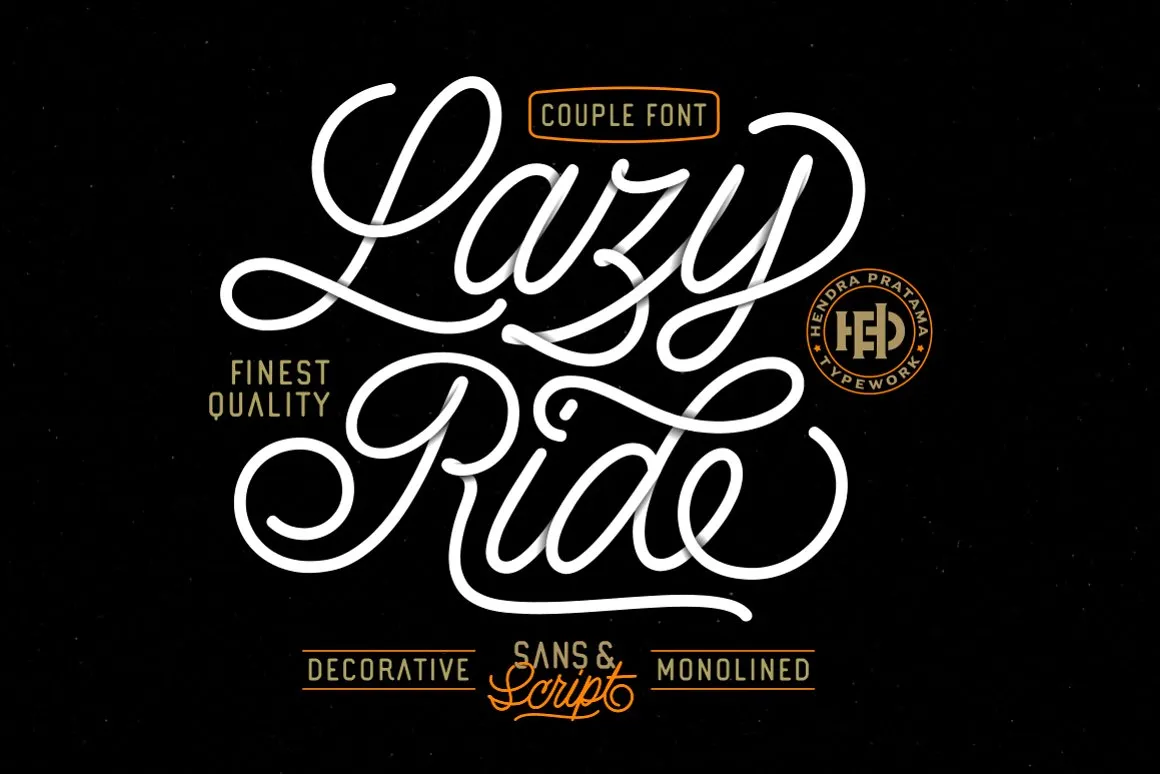
Descubra a nova adição para seus projetos de design com Lazy Ride Script Font, uma fonte script premium criada por Hendra Pratama que agora está disponível gratuitamente. Esta fonte é perfeita para aqueles que precisam dar um toque de ternura aos seus trabalhos. Ela combina muito bem com outras fuentes e pode adicionar o estilo necessário ao seu projeto. Lazy Ride Script contém mais de 670 glyphes, está disponível em formato OpenType e possui atribuição Unicode PUA (Personal Use Agreement). O uso alternativo dos glyphs é dividido em várias fechas de características do OpenType: Alterações Estilísticas, Características Contextuais, Espalhamento, Ligaturas e Conjunto de Alteração Estilística. No conjunto de alteração estilística, você pode selecionar até 21 versões alternativas para cada letra. Esta fonte é uma excelente escolha para aqueles que procuram adicionar um ar delicado a seus projetos gráficos. Com Lazy Ride Script Font na sua coleção, sempre terá o desenho perfeito para qualquer texto ou layout. Não deixe de aproveitar esta oferta especial agora e faça seu projeto brilhar com esta fonte única.